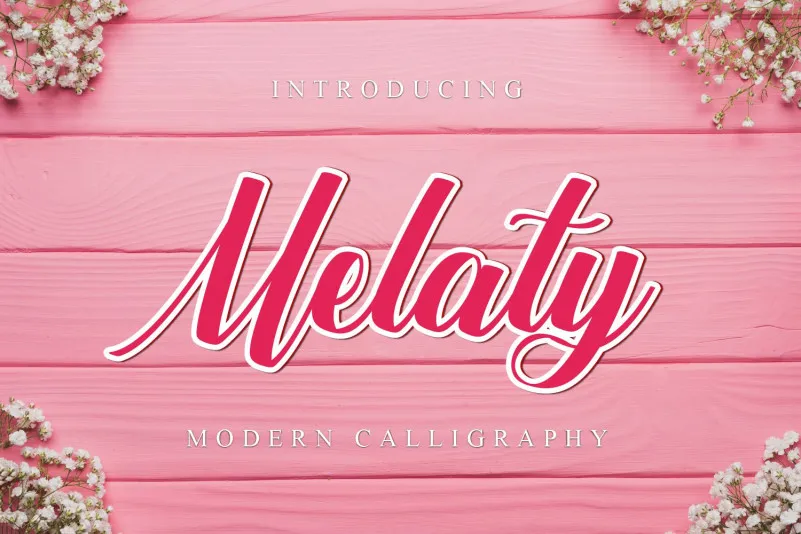
Melaty Font – Fonte Grátis
Melaty Font
Esta é uma fonte círconfusa e bela, projetada para expressar estilos pessoais com liberdade. É perfeita para criar designs únicos e delicados, como convites de casamento, cartas de agradecimento, anúncios de evento, cartões de felicitações, logotipos e muito mais. Suas ondulações elegantes permitem que qualquer projeto seja transformado em algo especial, tornando-a uma opção ideal para aqueles desejando um toque único e sofisticado nos seus projetos. Ideal para designers que valorizam personalização e elegância, a fonte Melaty é o complemento perfeito para seus próximos projetos de arte visual.